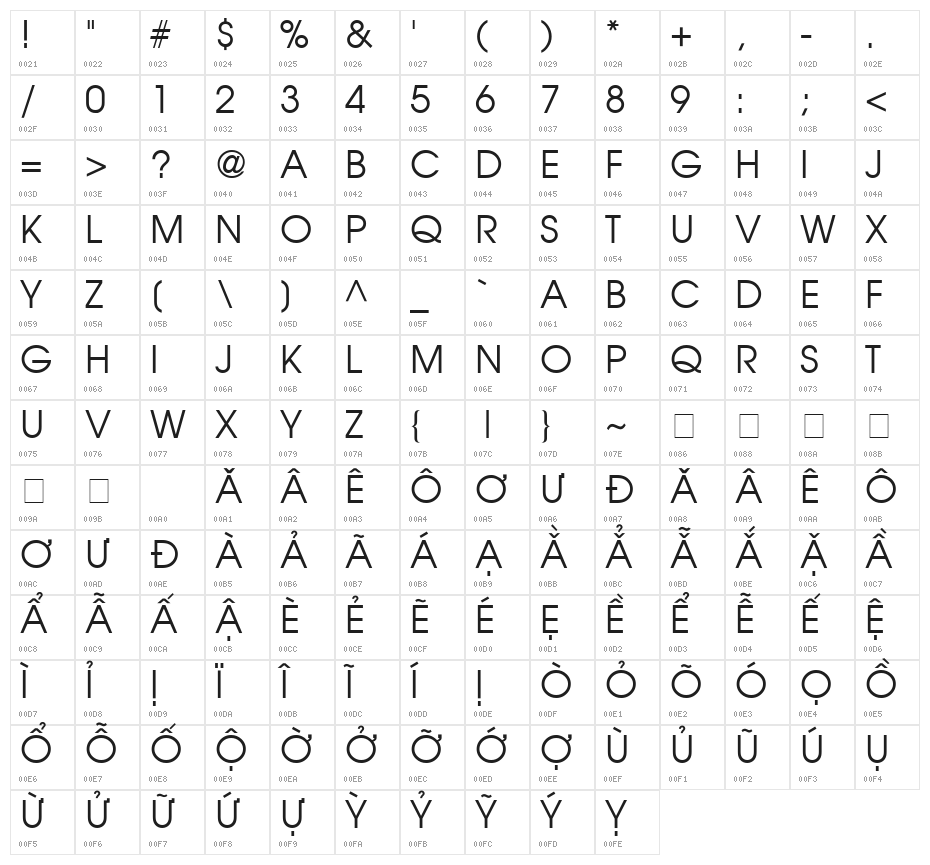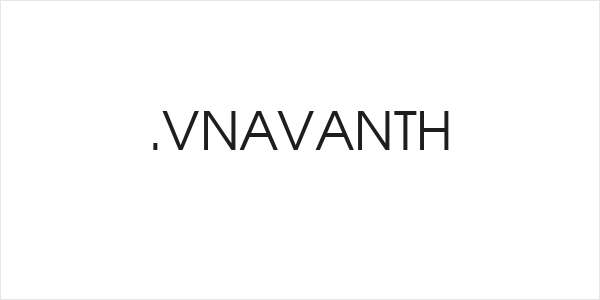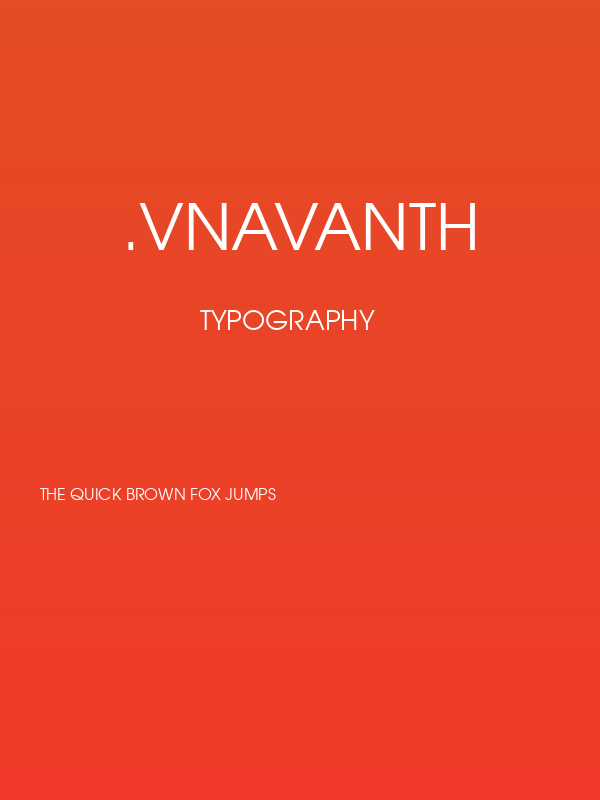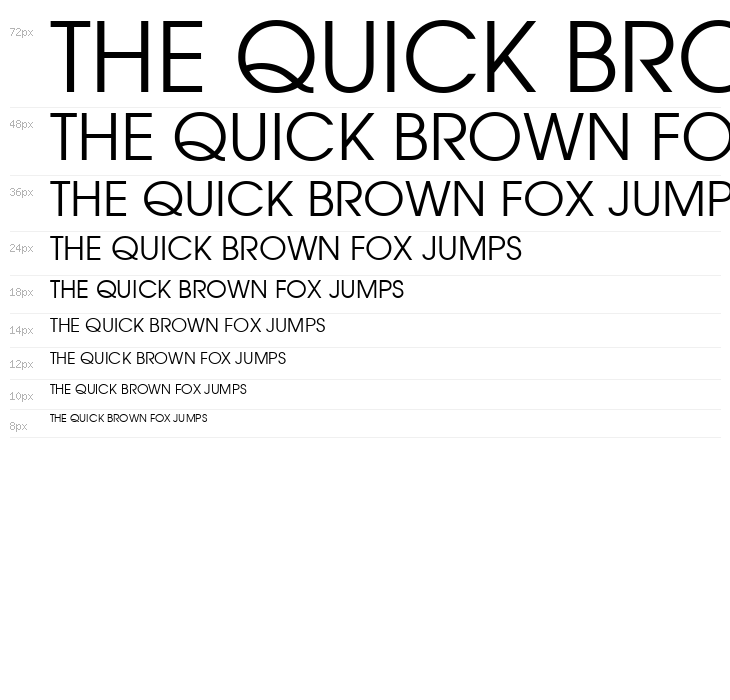
.VnAvantH Font
| Progetti proposti | Ideal for branding, corporate materials, web design, and editorial layouts where a clean and contemporary look is needed. |